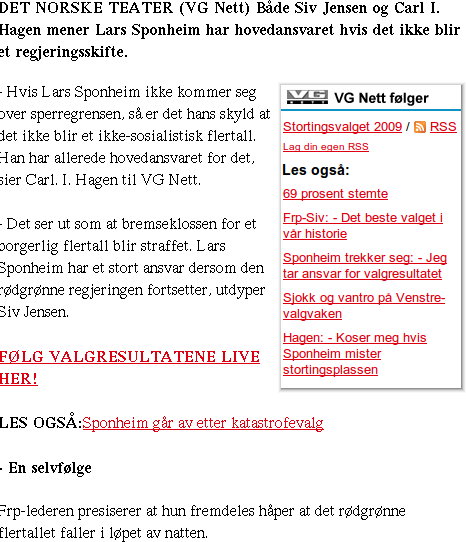
FrozenFish Skrevet 9. september 2009 Alle nettsider viser lesbare fonter, unntatt vg.no. Kan det være noe jeg har glemt å installere, tro? Trodde alt skulle være på plass med nyeste Ubuntu...
FrozenFish Skrevet 9. september 2009 Forfatter Skrevet 9. september 2009 Glemte å ta med at det er Opera jeg bruker....
flyndrefjes Skrevet 10. september 2009 Glemte å ta med at det er Opera jeg bruker.... Ser ut til at VG bruker disse fontene i utgangspunktet: body {font-family: "Lucida Grande", arial, sans-serif; font-size: 100%; Men, hva mener du med uleselig? Altså HELT uleselig? Ser det ut som "gresk" eller er det bare noe tull med font-størrelsen? Har du et bilde du kan laste opp hit? P.S. Bruker Opera 10 selv også i Ubuntu 8.04. Men har ingen problemer med VG. Så det er nok et visst håp om å få saken løst. Har du installert pakken: ubuntu-restricted-extras? Den inneholder en del font-typer som er gjengangere på internett.
FrozenFish Skrevet 14. september 2009 Forfatter Skrevet 14. september 2009 Nei, det er leselig, men veldig "hakkete" font... Har lagt ved screenshot.
stiber Skrevet 16. september 2009 Ta å sjekk font-opsettet på about:config (skriv inn i url feltet) Sjekk fanene "CSS Generic Font Family" og "Fonts" for ukjente fonter. Jeg måtte velge nye fonter for epost, pga. "hakkete" fonter.